Che font (o carattere) si usa nei libri?
Bella domanda!
Me la sono posto anch’io molte volte negli ultimi anni e, pur trovando mezze risposte qua e là, non sono riuscito a ritenermi soddisfatto finché non ho compiuto una delle mie lunghe crociate in merito.
Armato di pazienza, libri e scanner ho sfidato alla pugna le case editoriali, deciso a scoprire quale font utilizzassero per la stampa dei loro romanzi.
A metà dell’opera ho scoperto che molti editori inglesi si arrendono già alla prima pagina, sventolando una bandiera bianca con su scritto il carattere tipografico usato. Ovviamente gli editori italiani non sono così codardi, o forse sono solo più omertosi, e tengono la bocca chiusa dall prima all’ultima pagina.
Per vincerli mi sono affidato all’utile sito Identifont, che grazie a alcune domande mirate scova spesso il carattere usato nel libro, e in caso questo fallisse all’altrettanto utile Myfonts, su cui ho confrontato i paragrafi cartacei scannerizzati con i font digitali equivalenti.
Vi presento ora i risultati di questa lunga ricerca, e non solo a parole: per ogni libro analizzato ho preparato una immagine dove il carattere cartaceo precede quello digitale, di modo che possiate vedere coi vostri occhi di che font si tratti. E magari risparmiarvi una fatica simile nel futuro (sempre che ci siano altri folli come me in giro).
Ebbene, che carattere usano gli editori per stampare un libro?
Guanda
L’APOCALISSE RIMANDATA - Dario Fo
Font usato: Simoncini Garamond
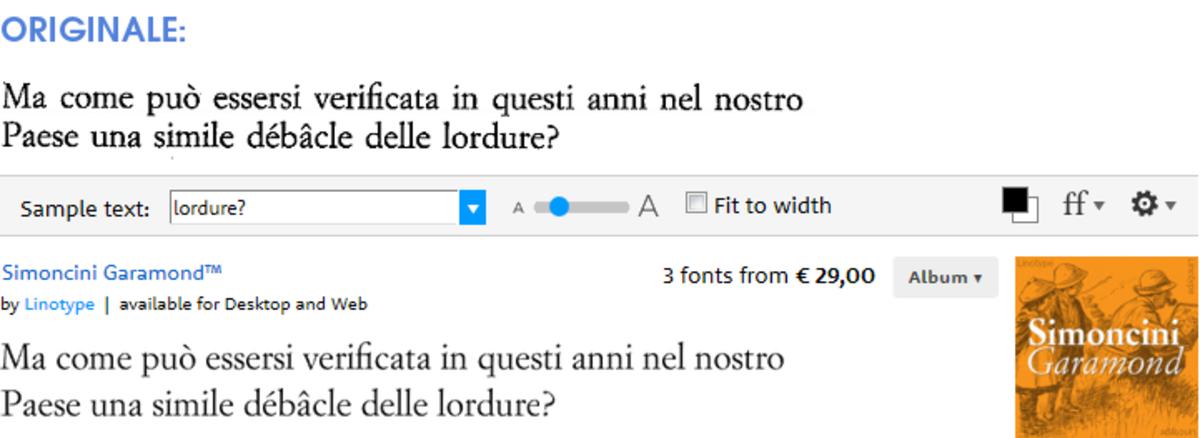
Booklet
EL MISTERIO DE LA CRIPTA EMBRUJADA - Eduardo Mendoza
Font usato: New Aster
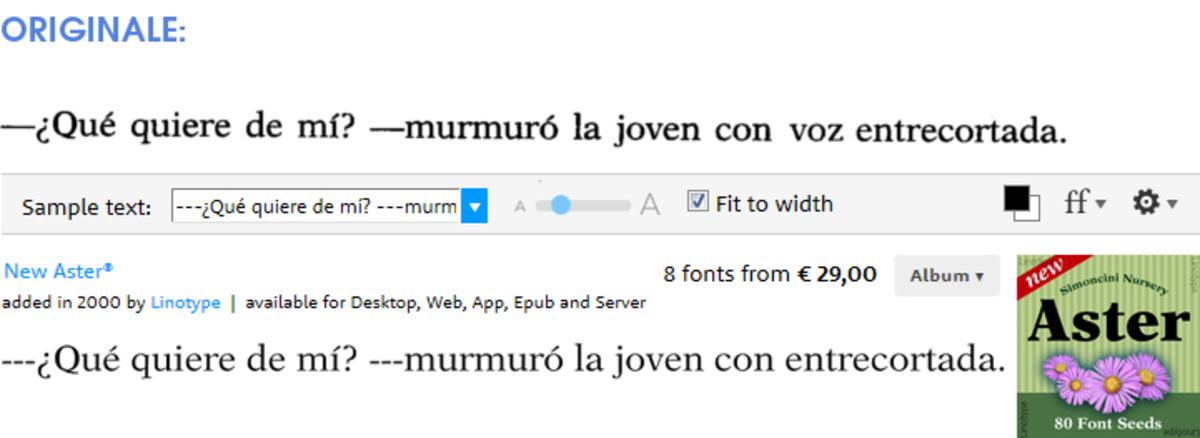
Harper Perennial
FLUKE - Christopher Moore
Font usato: Baskerville Original Pro
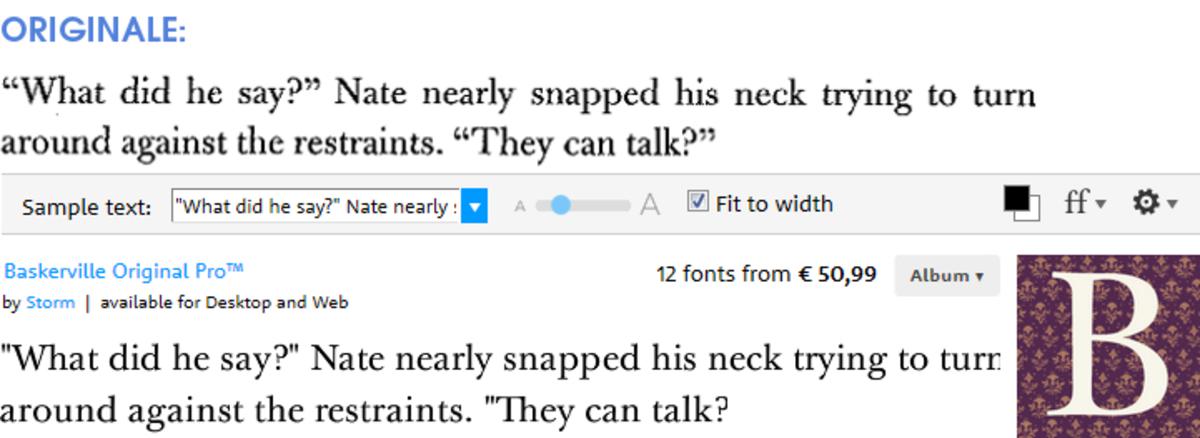
Debolsillo
REBELIÓN EN LA GRANJA - George Orwell
Font usato: Garamond Classico
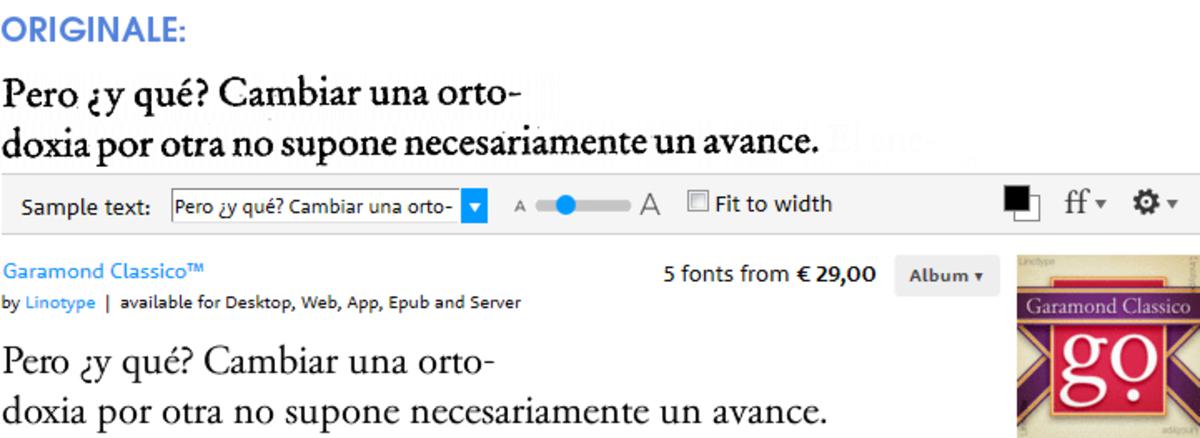
Adelphi
Il PIÙ GRANDE UOMO SCIMMIA DEL PLEISTOCENE - Roy Lewis
Font usato: Baskerville
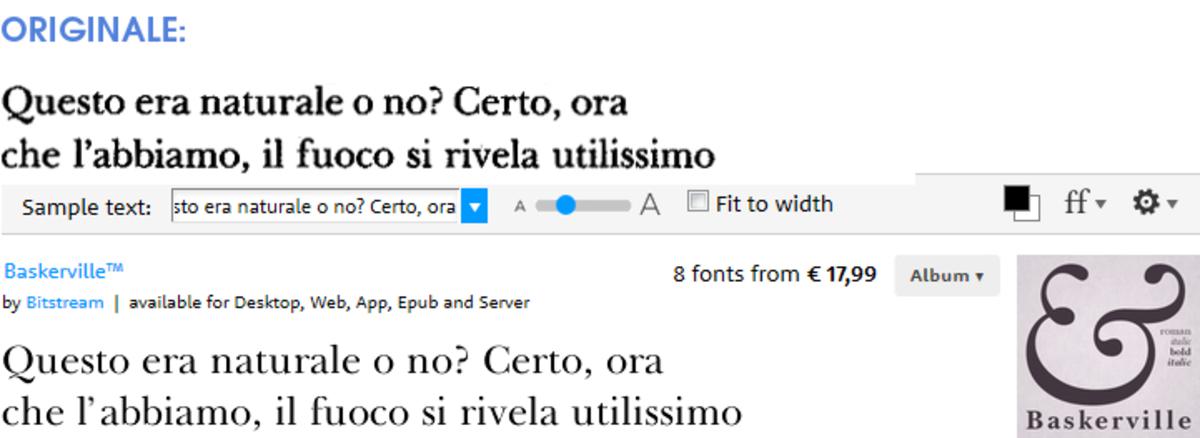
Feltrinelli
PULP - Charles Bukowski
Font usato: Simonicini Garamond
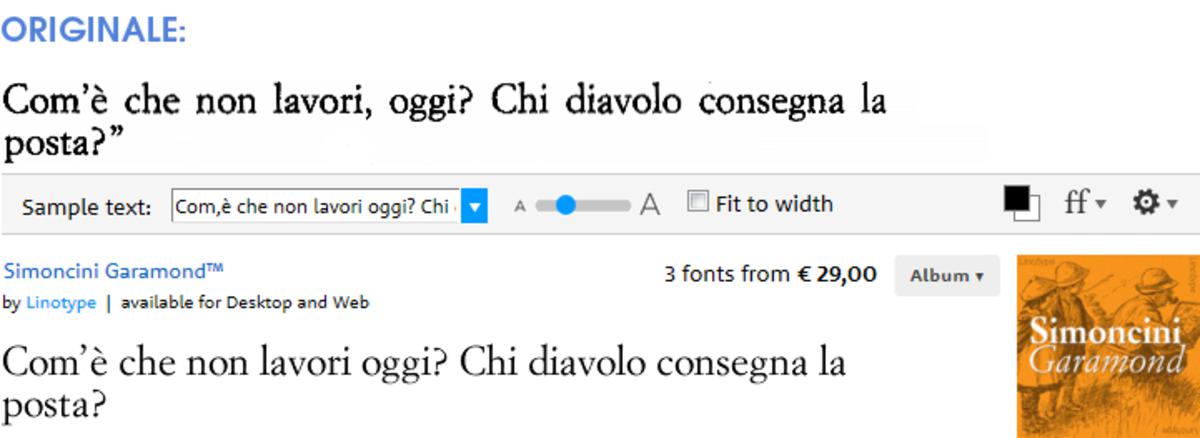
Edizioni E/O
L’ELEGANZA DEL RICCIO - Barbery Muriel
Font usato: Simonicini Garamond
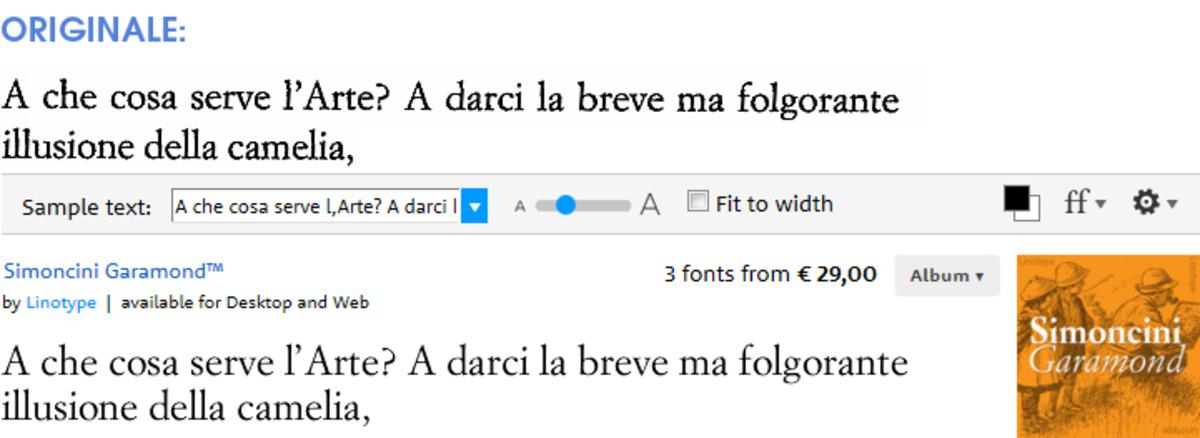
Vallecchi
TRISTE, SOLITARIO Y FINAL - Osvaldo Soriano
Font usato: Garamond 3
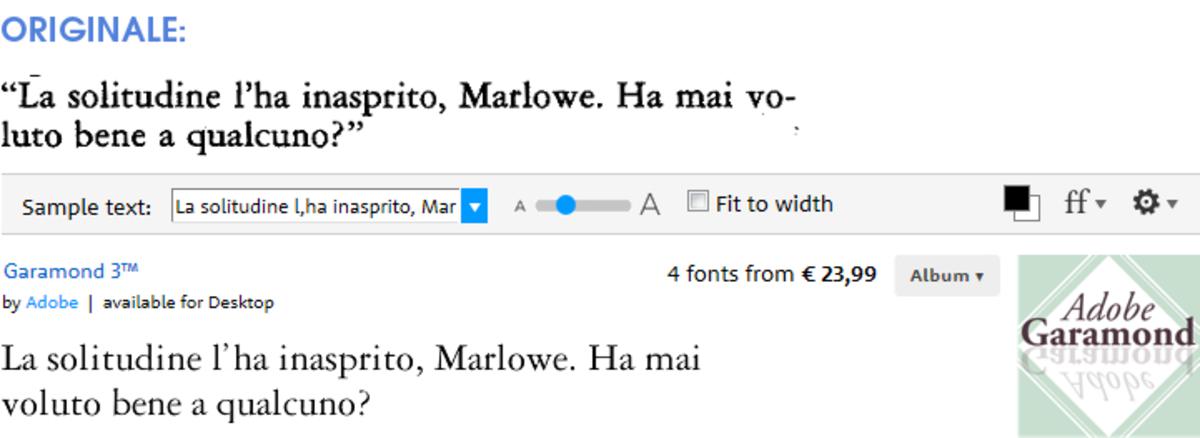
Bompiani
PIAN DELLA TORTILLA - John Steinbeck
Font usato: Garamond
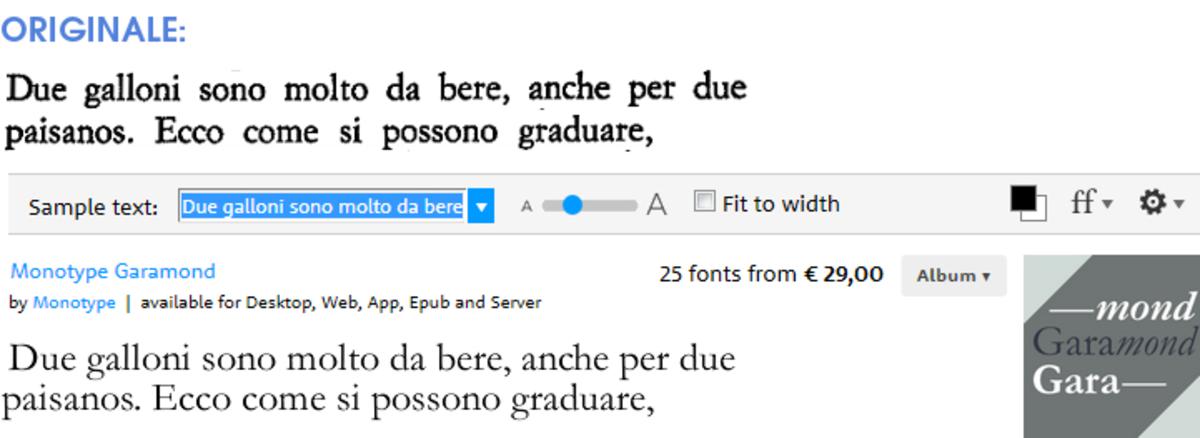
Mondadori
VERACRUZ - Valerio Evangelisti
Font usato: Palatino
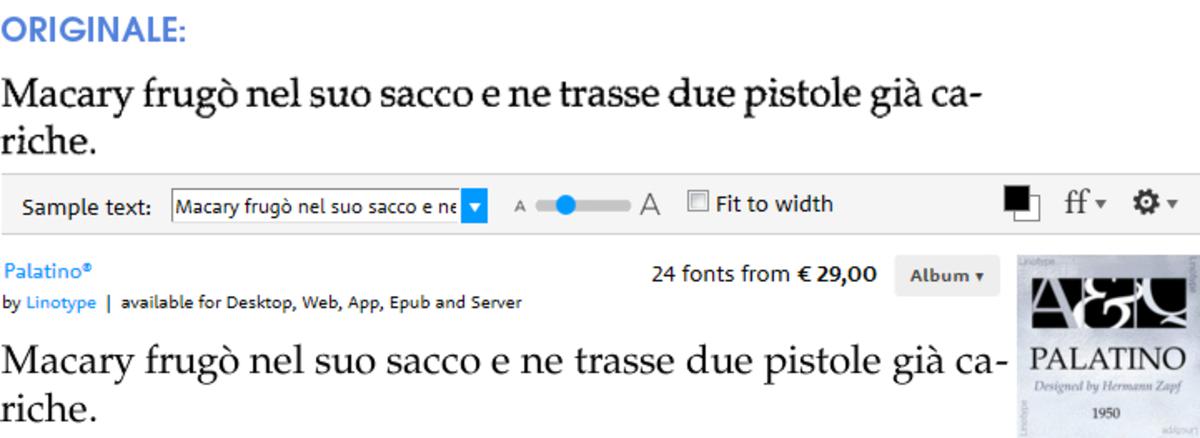
E ora una piccola carrellata dei libri di editori inglesi che sbandieravano il font utilizzato nelle prime pagine, una buona abitudine che spero possa diventare comune anche qui in Italia (e Spagna, e America… e perché no? in tutto il mondo).
Penguin
CANNERY ROAD - John Steinbeck
Font utilizzato: Bembo
Hodder & Stoughton
ONE DAY - David Nicholls
Font utilizzato: Sabon MT
Orbit
A DIRTY JOB - Christopher Moore
Font utilizzato: Palatino
Little, Brown
THE CASUAL VACANCY - J.K. ROWLING
Font utilizzato: Bembo
Abacus
ME TALK PRETTY ONE DAY - David Sedaris
Font utilizzato: Bembo Dante
Ecco qua.
Ora è tempo di trarre le conclusioni:
Possiamo notare che la stragrande maggioranza di editori italiani (stragrande almeno per quelli che avevo qui in casa, in Spagna) usa il font Garamond, in una qualunque delle sue versioni. Niente di nuovo sul fronte occidentale, ma almeno ora ne ho le prove!
Mondadori rema contro corrente usando lo splendido, a mio avviso, Palatino, e così fa anche la Orbit, una importante casa editrice inglese.
Nel Regno Unito sembra anche molto comune il font Bembo, anche solo per essere usato dal colosso Penguin, oltre che da Abacus e Little, Brown. (NdGatto, come fattomi notare nei commenti, Abacus non usa il font Bembo, bensì Dante. Essendo entrambi tratti dai lavori di Francesco Griffo, però, ai fini di questa lista il risultato è lo stesso. Vale lo stesso che per Sabon e New Aster, di cui parlo tra due paragrafi)
Adelphi e Harper Perennial si affidano al classicissimo Baskerville, seppur in versioni differenti.
Gli ultimi rimasti Sabon e New Aster, invece, possono quasi considerarsi Garamond a loro volta, giacché il primo è opera di un allievo di Claude Garamont in persona, e il secondo è stato disegnato da Francesco Simoncini, che ha tratto ispirazione dal maestro rinascimentale in tutti i suoi lavori più importanti.
Tirando le somme Garamond risulta essere il font più utilizzato per la stampa di libri e romanzi, quale che sia la versione. Secondo troviamo Bembo, altro font d’ispirazione rinascimentale, molto usato soprattutto all’estero. Infine Palatino, un font equilibrato e dal gusto più moderno, senza legature et similia; e Baskerville, font dal gusto retro che continua a essere molto utilizzato.
Quindi che dire?